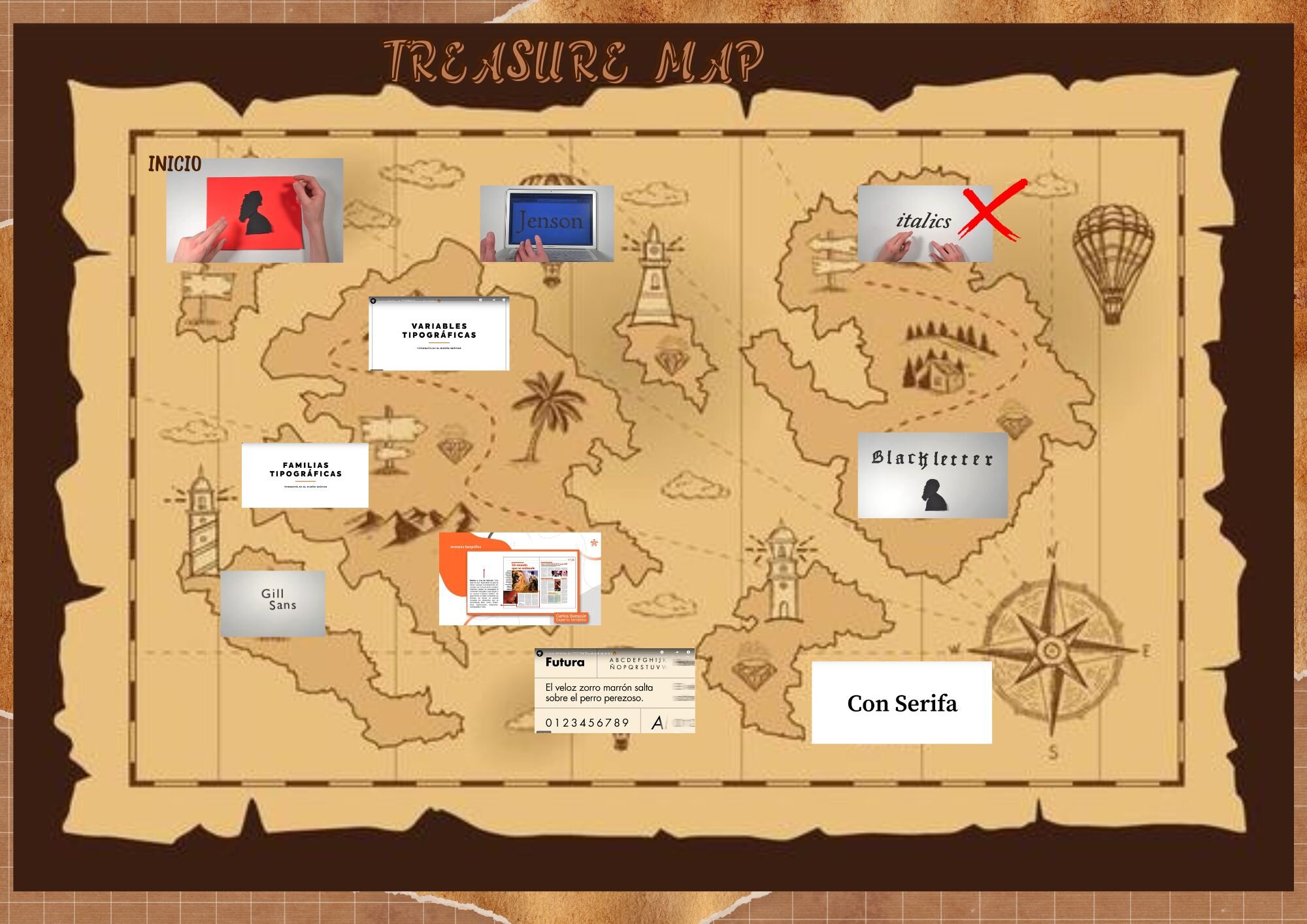
Mapa del tesoro sobre las tipografías.
Identifica los conceptos o preguntas con las imagenes
Mapa del tesoro sobre las tipografías.
Identifica los conceptos o preguntas con las imagenes
1 ¿Quién es Johannes Gutenberg? 2 ¿Cuál es la tipografía sin serifa? 3 ¿Quién creo la tipografía Roman Type? 4 ¿Cuál de las imágenes tiene este concepto: 5 ¿Cuál es el nivel terciario? 6 ¿Quién creo el tipo de letra Humanist Sans? 7 ¿Cuál de las imágenes tiene este concepto: 8 Remates en los extremos de los trazos. 9 1ra letra creada por la escritura de los monjes. 10 ¿Cuáles son las letras cursivas?